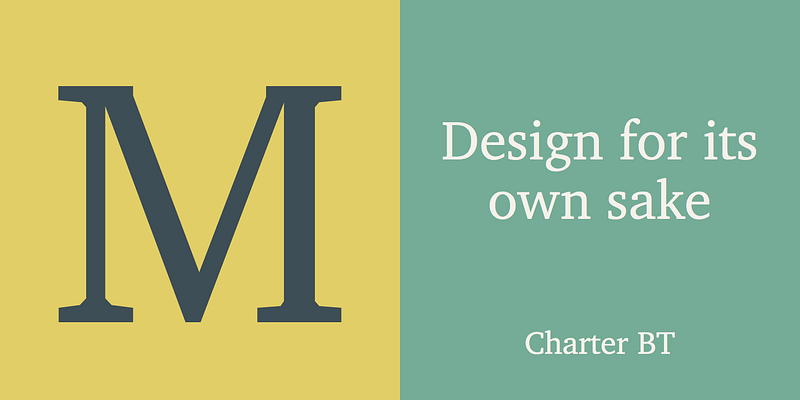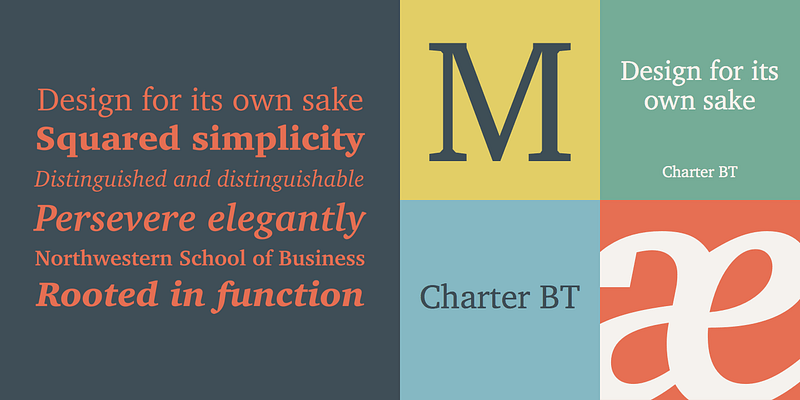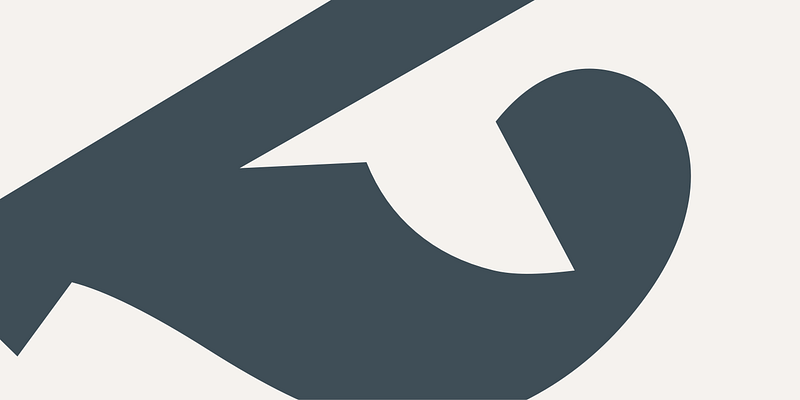
Initialement publiée en 1987, Charter présente trois caractéristiques importantes : une largeur de police compacte pour un ajustement économique ; une hauteur d’x généreuse pour une meilleure lisibilité en petits corps ; et des polices de caractères robustes et ouvertes pour une reproduction fiable, aussi bien en typographie qu’en imprimante laser. Ce design apporte clarté et fraîcheur aux documents courants, tels que les bulletins d’information, les manuels scolaires, les annuaires et les manuels techniques, où la concentration du lecteur ne doit pas être perturbée par des polices inhabituelles, mais où la monotonie typographique peut nuire à la compréhension. L’italique, dont les lettres sont cursives, est immédiatement reconnaissable, tout en étant suffisamment lisible pour un texte continu. Charter BT Pro Pack propose six polices : romaine, italique, gras, gras italique, noir et noir italique. Ces polices incluent des caractères initialement développés pour les polices expertes, tels que les ligatures, les ornements, les chiffres anciens, les petites capitales et les lettres supérieures. Les polices Pro Pack prennent en charge les langues d’Europe occidentale, centrale et orientale. Les polices OpenType sont un format multiplateforme. Une même police OpenType peut être installée sur les systèmes MAC OS X, Windows, Linux et Unix. MAC OS X, Windows 2000, XP et Vista prennent en charge OpenType de manière intégrée. Les polices OpenType fonctionnent également sur Linux, Unix et les versions antérieures de Windows, où elles sont reconnues comme des polices TrueType. OpenType offre bien plus de fonctionnalités que les formats TrueType et PostScript standard, notamment la possibilité d’installer la même police sur différentes plateformes, essentielle à la portabilité des documents. Les polices OpenType améliorent la productivité, car les graphistes et les professionnels n’ont plus à gérer de nombreuses polices différentes. Avec OpenType, les clients disposent de jeux de caractères plus étendus et d’un nombre réduit de fichiers de polices à gérer.